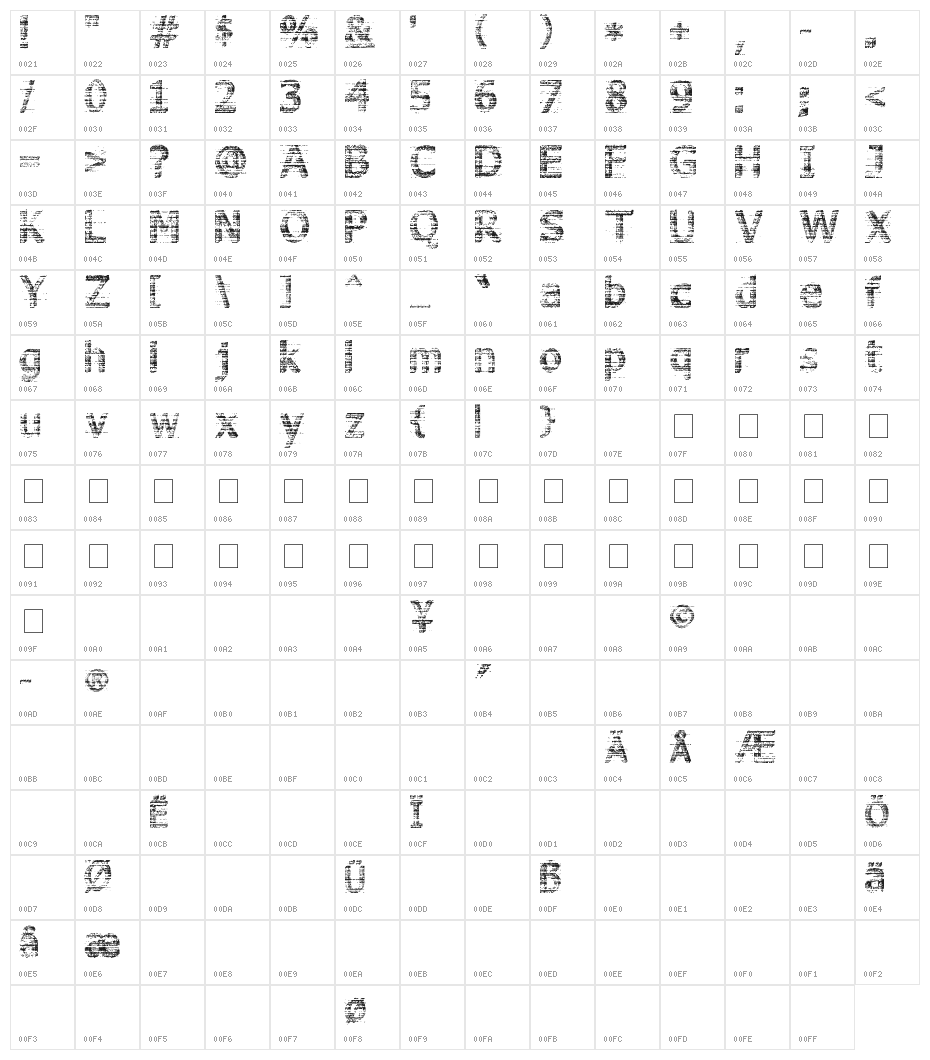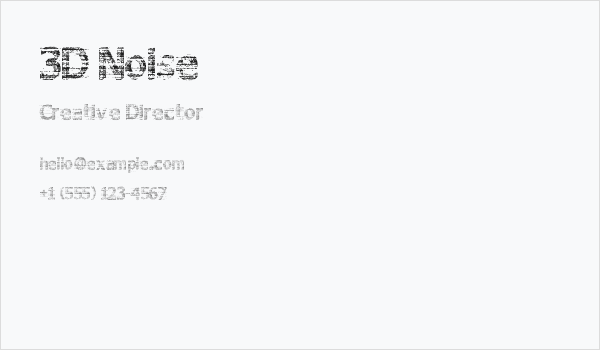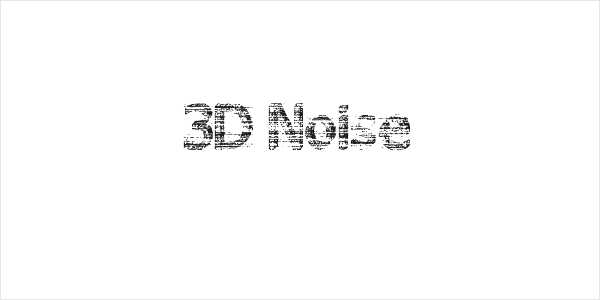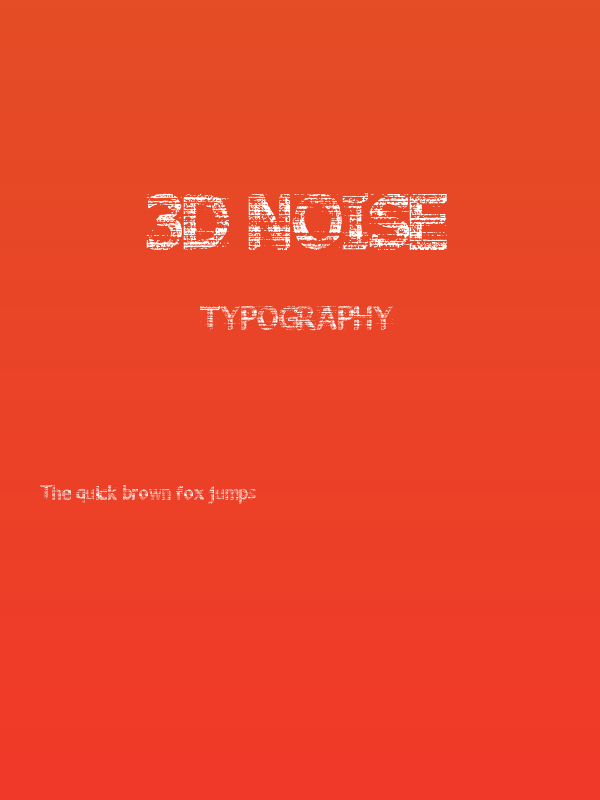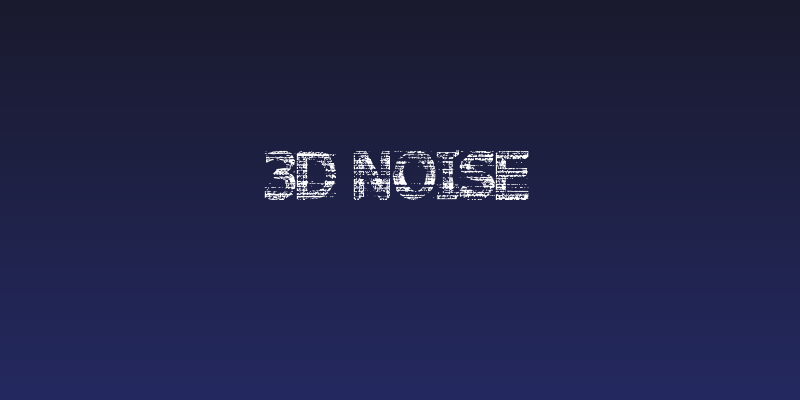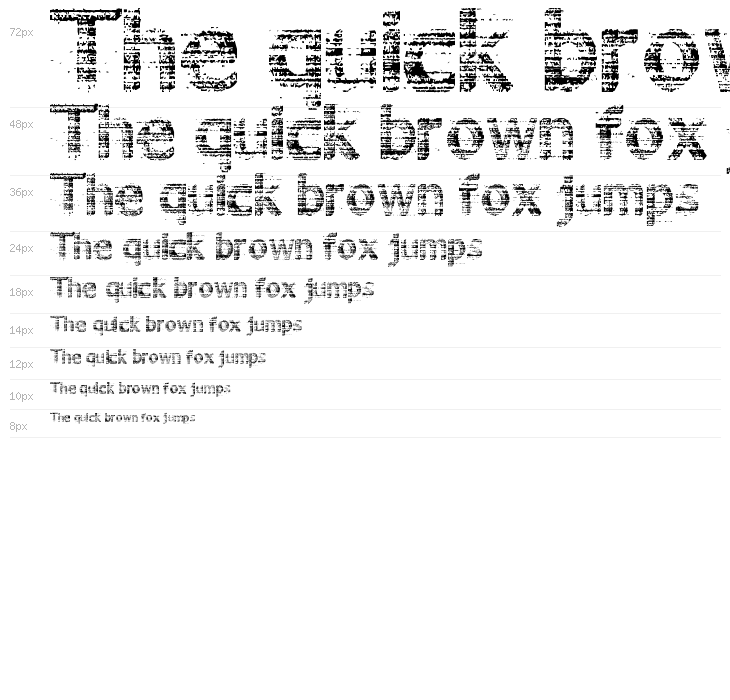
3D Noise Font
✎ Distorted Eroded
| Kategorien | Distorted Eroded |
| Gesamtstil | Modern, Industrial |
| Vorgeschlagene Projekte | Perfect for album covers, posters, urban-themed designs, and branding that requires a strong, edgy look. |